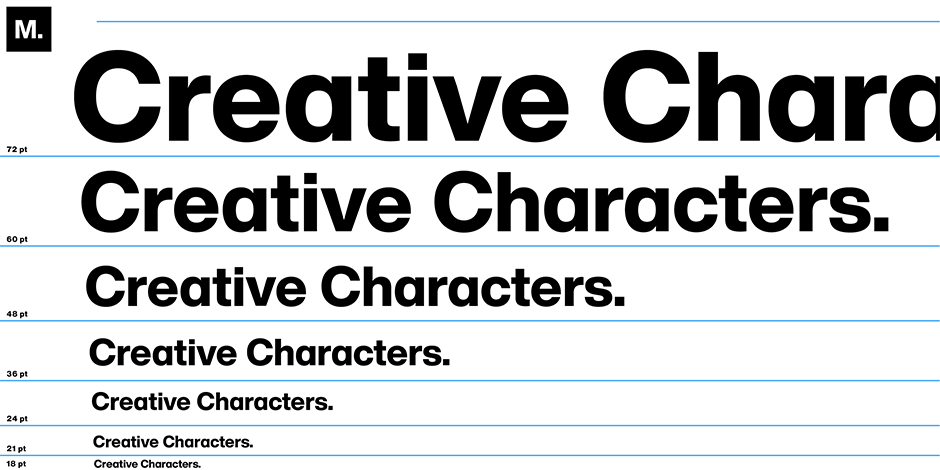
Les créatifs.
Exemple de texte "Les créatifs" affiché dans une police sans sérif en gras dans plusieurs tailles de points allant de 18 pt à 72 pt, aligné sur des lignes de base horizontales bleues sur un fond blanc. Chaque taille est étiquetée en conséquence, ce qui met en évidence la cohérence et la clarté de la policeà différentes échelles.
Rencontrez les personnes qui créent certaines des œuvres les plus passionnantes d'aujourd'hui.
Les créatifs vous propose des entretiens et des discussions avec certaines des personnes les plus intéressantes travaillant dans le domaine du design et de la typographie aujourd'hui. La série a été lancée sur MyFonts il y a plusieurs années, et nous la ramenons aujourd'hui avec quelques nouveaux tours dans son sac.
Nouvelles publications sur Police : Interviews en profondeur.
Vous avez déjà voulu en savoir plus sur une nouvelle version de police : quel est le processus, quel est le raisonnement derrière la conception ? C'est l'occasion ou jamais ! Écoutez les concepteurs eux-mêmes et découvrez de l'intérieur le processus de publication d'un nouveau site police.
Dans cette interview, nous parlons avec Mark Simonson de son parcours dans la création de son nouveau site police, Proxima Sera. Écoutez Mark.
À l'intérieur du studio : Les créatifs.
Grâce à des questions-réponses rapides et perspicaces, Inside the Studio : Les créatifs. Tous les deux mois, nous jetterons un coup d'œil à l'intérieur de fonderies classiques et expérimentées du monde de la création typographique. Rejoignez-nous pour un regard plus approfondi sur le monde fascinant de la création de caractères, du point de vue des designers et des studios, afin de découvrir les travaux et les caractères passionnants qui sont en train d'être créés.
Giuseppe & Paco
En discutant avec Giuseppe Salerno, 43 ans, et Paco Gonzalez, 46 ans, de Resistenza (résistance) Type Foundry, basés à Turin, en Italie, et à Valence, en Espagne, Giuseppe Salerno et Paco Gonzalez, partenaires concepteurs de police, vous aurez droit à une leçon d'histoire du lettrage. Les deux hommes se consacrent à la production de caractères selon un processus artisanal - en créant des lettres à la main par le biais de la calligraphie - avant de numériser le site polices pour le marché contemporain. En savoir plus
Santi Rey
En 2014, le créateur de caractères espagnol Santi Rey, aujourd'hui âgé de 35 ans, a quitté sa ville natale de Madrid pour Londres. Bien que parlant peu l'anglais à l'époque, il était déterminé à explorer de nouvelles possibilités d'emploi et à élargir ses horizons. C'est à cette époque que Santi a découvert sa passion pour la typographie et le design de marque, ainsi que son amour pour l'élaboration d'histoires d'origine convaincantes pour son site polices... En savoir plus
Julien Fincker
À l'approche de la trentaine, le graphiste et créateur de caractères Julien Fincker, de Stuttgart, en Allemagne, célèbre l'expression personnelle qu'il a trouvée grâce à sa fonderie éponyme pour le travail du bois, la gravure et, surtout, la création de police . En savoir plus
Daniel Pelavin - Pelavin Polices
En discutant avec l'illustrateur et typographe Danny Pelavin, vous découvrirez qu'il est reconnaissant d'avoir atteint l'âge de la créativité dans les années 1970, à l'époque des studios de design de Détroit ; qu'il réalise encore tous ses lettrages à la main ; et qu'il n'hésite pas à partager ses vérités. En savoir plus
Fitriyawan Runsell - Type de Runsell
Le créateur de caractères et de graphiques Fitriyawan Runsell, fondateur de Runsell Studios, a lancé son entreprise basée à Magelang City, en Indonésie, en 2016, alors qu'il n'avait que 24 ans. Depuis, il a créé plus de 300 polices dans plusieurs langues, de l'arabe à l'anglais. Récemment, sa fonderie s'est agrandie en introduisant Logofonts, une nouvelle division produisant des logos de marque pour les petites et moyennes entreprises. En savoir plus
Up and Coming Les créatifs.
Par le biais de questions-réponses rapides et perspicaces, la série Up and Coming Les créatifs vous présentera tous les deux mois des visages nouveaux et émergents dans le monde de la création typographique. Cette série couvrira le monde entier, mettant en lumière des designers et des studios qui réalisent des travaux passionnants et changent la façon dont les caractères sont créés.
Aldy Sidik - Type d'olive
Si chaque fonderie a une ambiance, celle d'Olivetype est jeune, urbaine et funky, avec une prédilection pour les graffitis polices. Fondée en 2019 par Aldy Sidik et Nurul Hidayani, une équipe mari-femme animée par ce que Sidik appelle "une passion commune pour la typographie", Olivetype est basée à Java Ouest, en Indonésie, sur une île entourée de volcans, dont certains sont en activité. En savoir plus
Cette semaine, nous parlons avec Jessica McCarty de son parcours en tant que dessinatrice de caractères et de ses conseils aux nouveaux dessinateurs. Écoutez Jessica.
Cette semaine, nous parlons avec Nicky Laatz de son parcours en tant que dessinatrice de caractères et de ses conseils aux nouveaux dessinateurs. Écouter Nicky